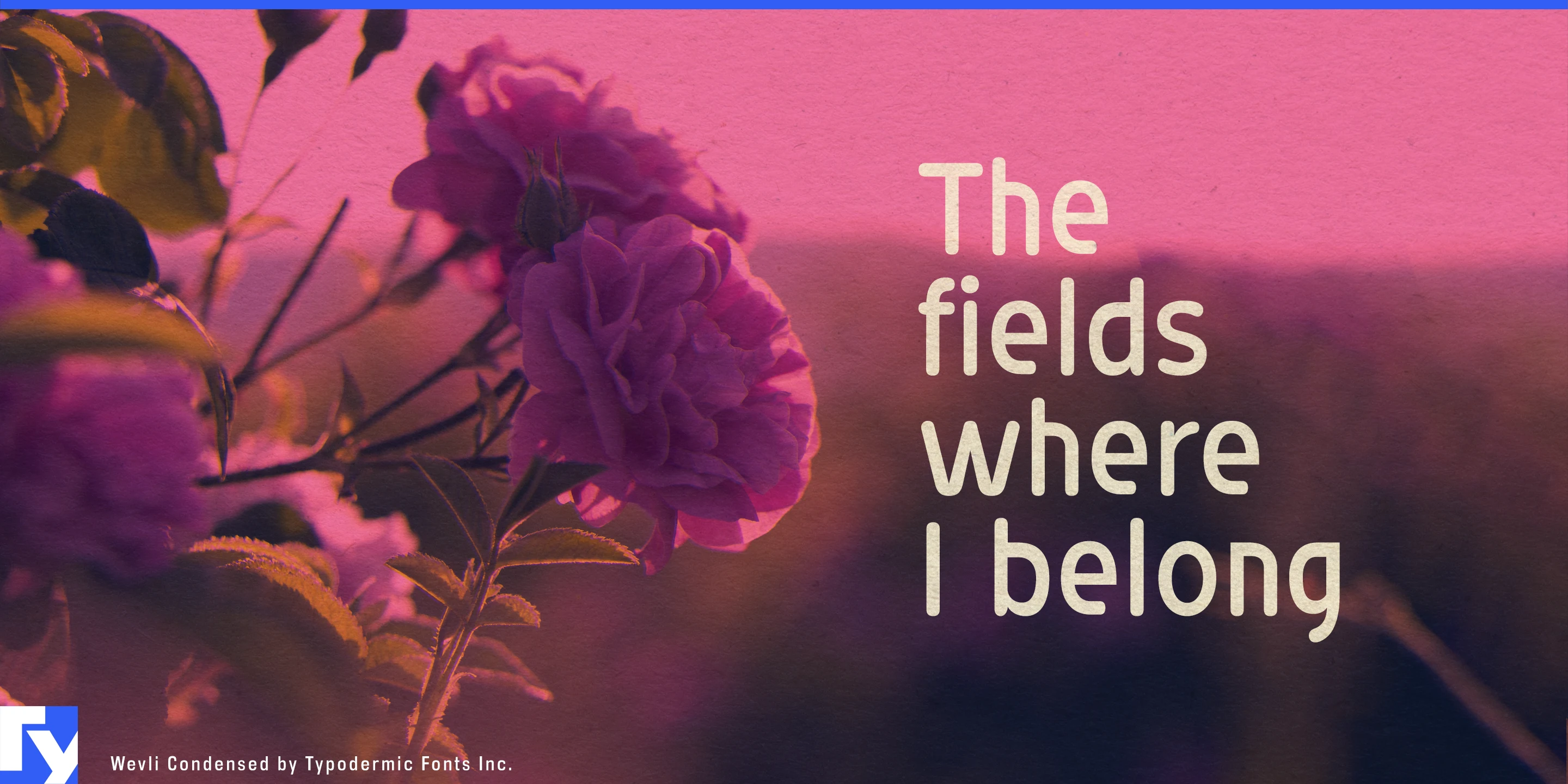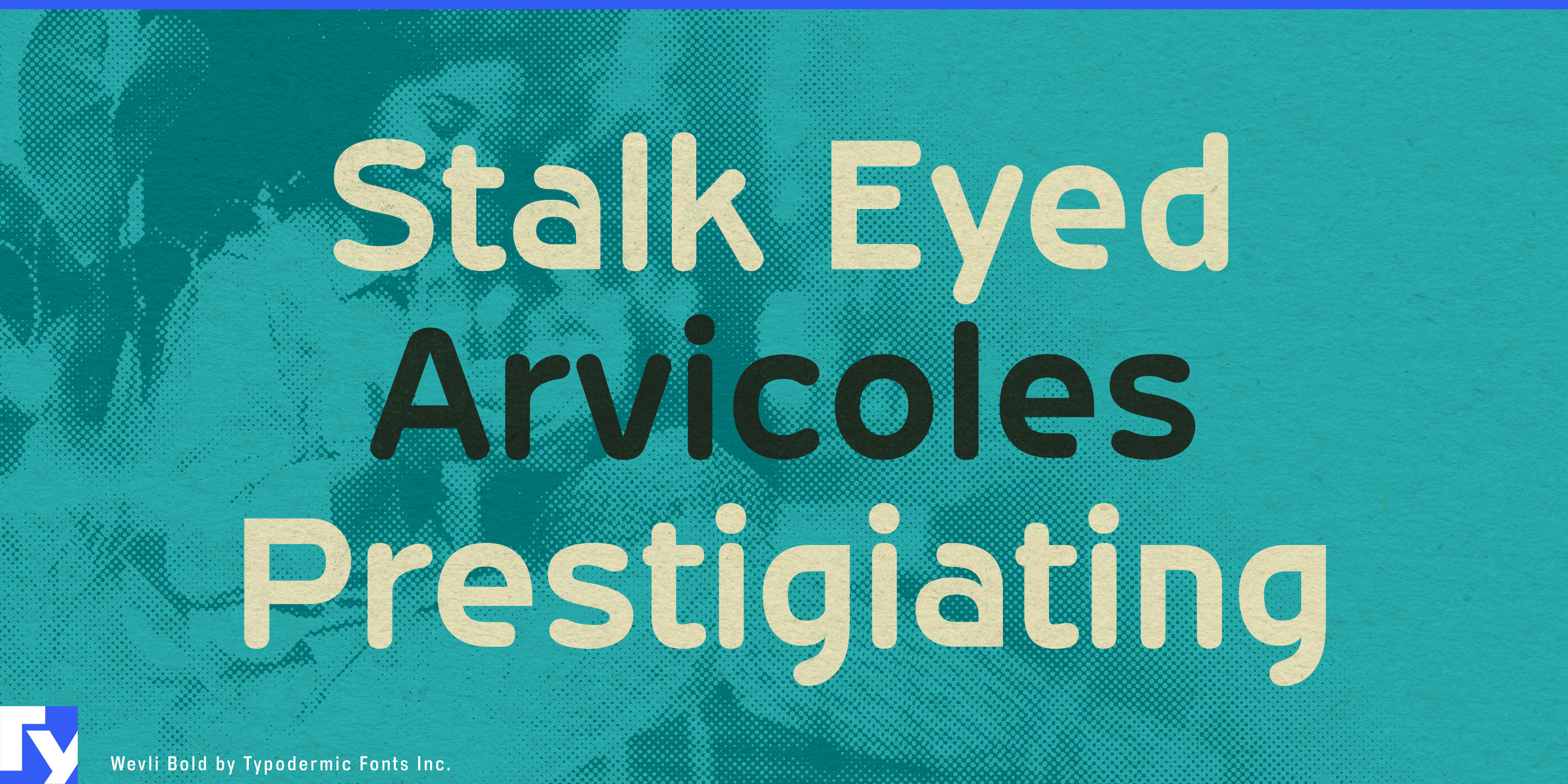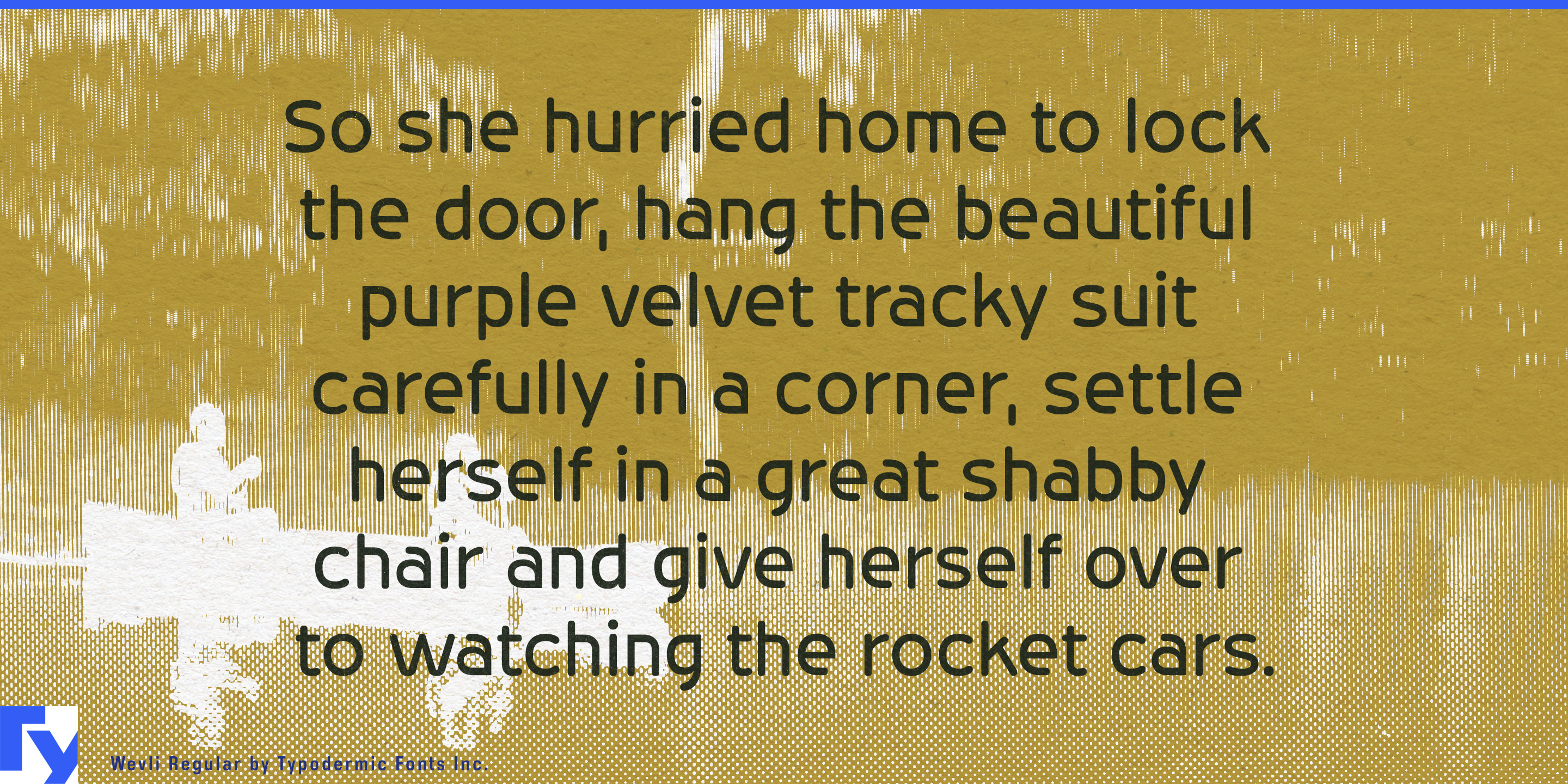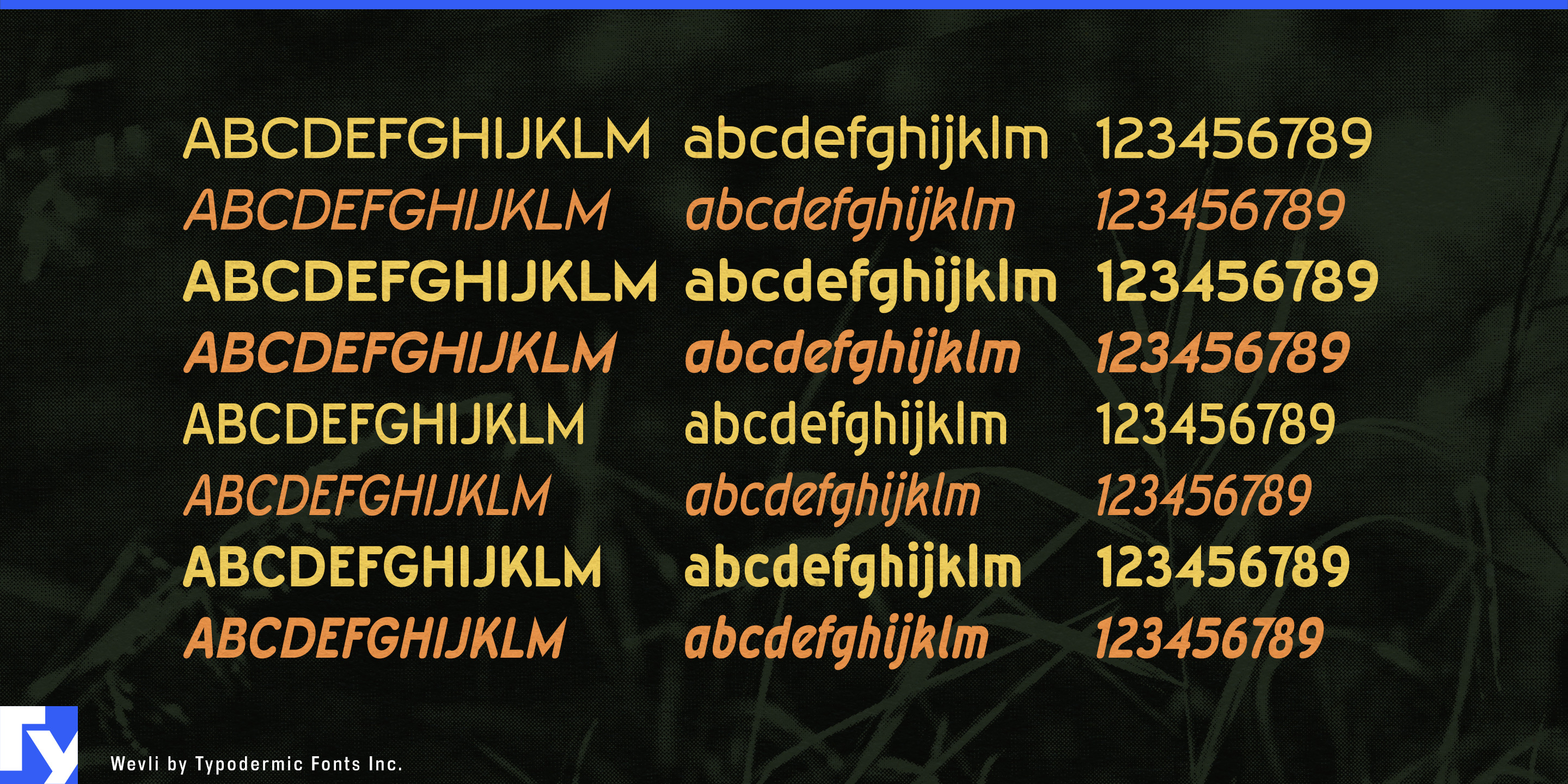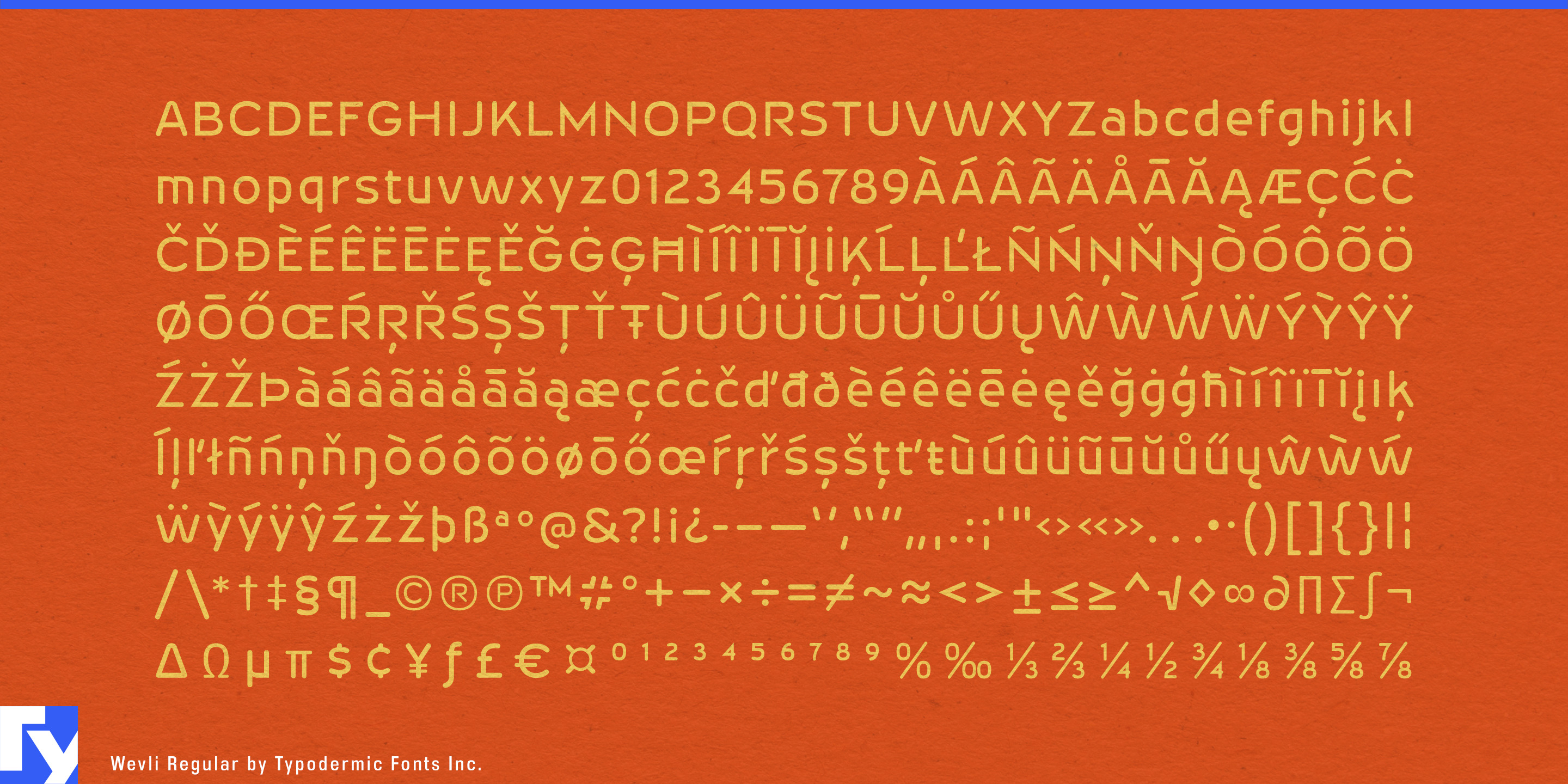
Wevli
Recrear el diseño de finales del milenio puede ser más difícil de lo que parece. Hoy se recuerda la época por sus ingredientes más estridentes: cromados, burbujas, píxeles, letras líquidas e interfaces agresivamente futuristas. Pero gran parte del mundo visual que rodeaba esos elementos era más corriente. Los centros comerciales, mostradores de comida rápida, aparatos electrónicos portátiles, revistas juveniles, salones recreativos y envases de software necesitaban una tipografía que pareciera nueva sin parecer ciencia ficción. Wevli procede de ese lado menos exagerado de la época.
Su estructura geométrica sin remates mezcla formas redondeadas con esquinas abruptas y cortes angulares. Las curvas pueden parecer suaves e informales en un momento y terminar con una precisión sorprendente al siguiente. Esa tensión da a Wevli un carácter ligeramente tecnológico sin atarla a terminales, píxeles, maquinaria ni ninguna convención futurista concreta. Como el propio diseño procede del cambio de milenio, lleva la mezcla particular de informalidad y experimentación geométrica de la época sin reconstruirla a partir de clichés Y2K contemporáneos.
Eso la hace especialmente útil para objetos de utilería de época y marcas ficticias. Las películas, juegos, exposiciones y producciones televisivas ambientadas en esos años necesitan más que letras espectaculares para títulos: necesitan la capa comercial cotidiana que hace convincente el entorno. Wevli puede componer letreros de restaurantes ficticios, promociones de centros comerciales, gráficos de salones recreativos, marcas de artículos deportivos, envases de aparatos electrónicos portátiles, anuncios de revistas, cajas de software, tableros de menús y etiquetas de productos sin hacer que cada objeto parezca retro de forma deliberada.
El mismo lenguaje visual funciona naturalmente en comida informal y ocio: hamburgueserías y tiendas de sándwiches, mostradores de pizza, envases de aperitivos, boleras, pistas de patinaje, salones recreativos, centros de laser tag y tiendas de skate. También conviene a temas de los primeros años digitales, como consolas portátiles, equipos de música compactos, cámaras digitales, auriculares, accesorios de juegos y aparatos de plástico translúcido.
Wevli sirve para algo más que palabras destacadas. Su estructura relativamente convencional y su espaciado abierto permiten componer descripciones de menús, textos breves de envases, pies de exposiciones, entradillas de revistas, diálogos de juegos y otros pasajes cortos con más carácter que una sans neutra de apoyo. Los estilos condensados extienden ese vocabulario a letreros estrechos, etiquetas, información de precios y composiciones promocionales compactas. Wevli funciona mejor cuando un diseño necesita la atmósfera comercial del cambio de milenio y no sus clichés más obvios.
- Primera publicación
- 2002
- Estilos
- 9 estilos
- Clase
- Sin remates
- Forma
- Geométrica, Redondeada
- Anchura
- Mixta
- Sistemas de escritura
- Latino
- Uso
- Uso destacado